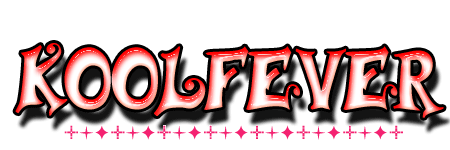
รับทำอักษรเยลลี่นะจ๊ะ
น่ารักมากค่ะ เค้าหวังดีมากเลยค่ะ  ขยันด้วย เก่งด้วย  มั่นด้วย :22:
(บางคนที่ไม่รู้ว่าจะเอาไว้ไปทำอะไร หรือว่า ไม่ชอบเนี่ยก็ไม่เป็นไรเน้อ)
แต่ลั่นว่า น่ารักดี เน้อ  :43: ไม่มีได หรือ เว็บ เอาเก็บไว้ดูเล่น ละกัน  :33:
ชื่นชมนะค่ะ  :33:
น่ารักมากค่ะ เค้าหวังดีมากเลยค่ะ  ขยันด้วย เก่งด้วย  มั่นด้วย :22:
(บางคนที่ไม่รู้ว่าจะเอาไว้ไปทำอะไร หรือว่า ไม่ชอบเนี่ยก็ไม่เป็นไรเน้อ)
แต่ลั่นว่า น่ารักดี เน้อ  :43: ไม่มีได หรือ เว็บ เอาเก็บไว้ดูเล่น ละกัน  :33:
ชื่นชมนะค่ะ  :33:
เอามั่ง
ได้แล้วค่ะ
ผิดตรงไหนบอกด้วยนะคะ
ให้ +1 เพราะความพยายามทำ  :30:
โอ้ววววว  :30:
เจ๋งจริงๆ  :30:
แต่เล่นเอาเครื่องสะดุดเลยแฮะ  :44:
สวยค่ะ  :25:
สวยดีครับ :45:
แล้วจะเอาไอ้ดึกดึ๋ยนี่ไปทำอะไร ยังนึกไม่ออก  :09: